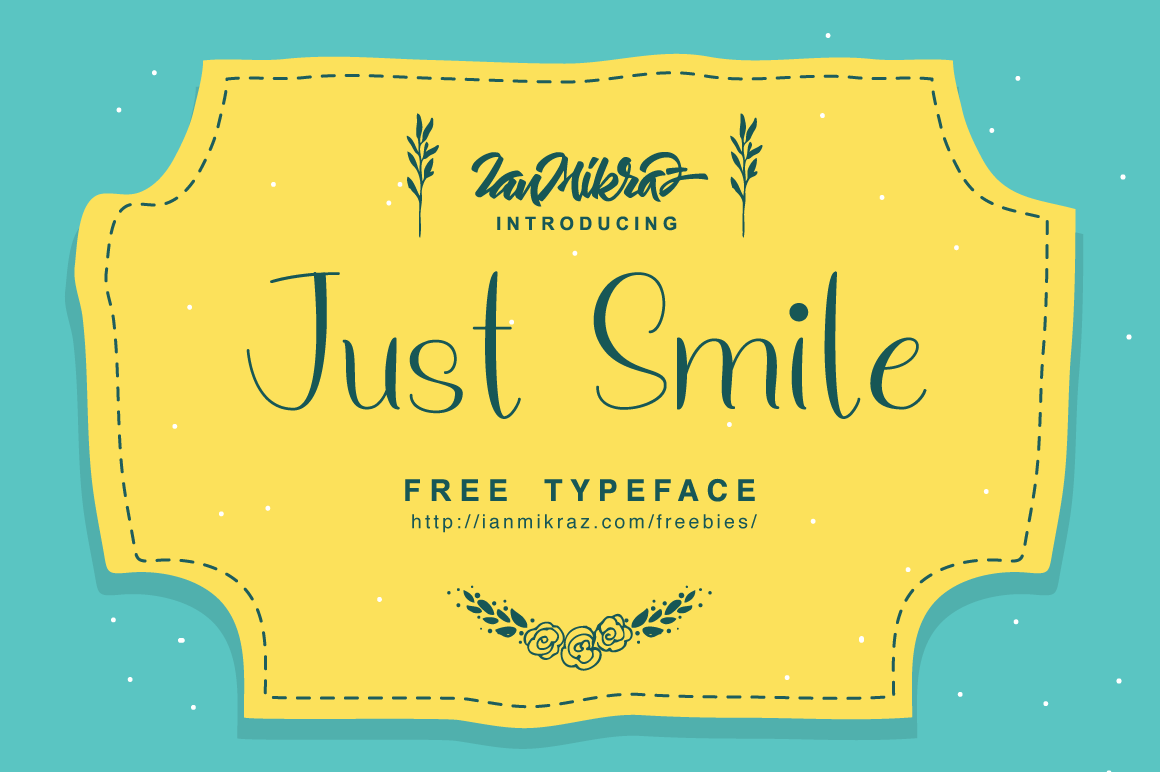
Just Smile Typeface – Download Grátis
“Com certeza, quando vemos a fonte Just Smile Typeface, logo nos vem à mente uma expressão leve e positiva — alegria pura, iluminando qualquer design. Esta fonte foi criada por IanMikraz e representa o espírito do bem que desejar convidar para todos os projetos de design. Ideal para um estilo de arte pessoal ou natural, como as etiquetas de moda, cartões de felicitações, até mesmo pintura, a Just Smile é uma fonte perfeita para quem busca uma personalidade e um toque natural em seus trabalhos. Sem dúvida, ela se torna o selo da alegria em qualquer projeto design que você iniciar.”